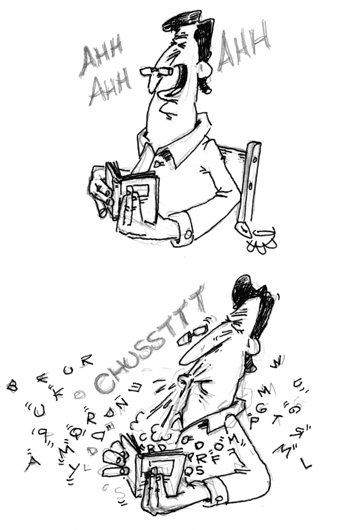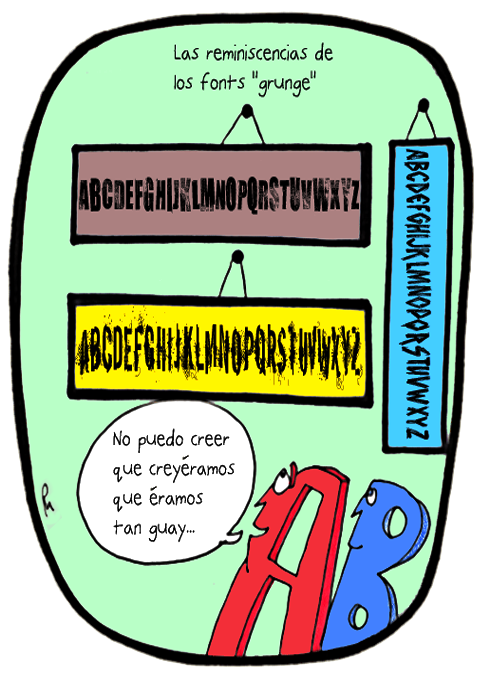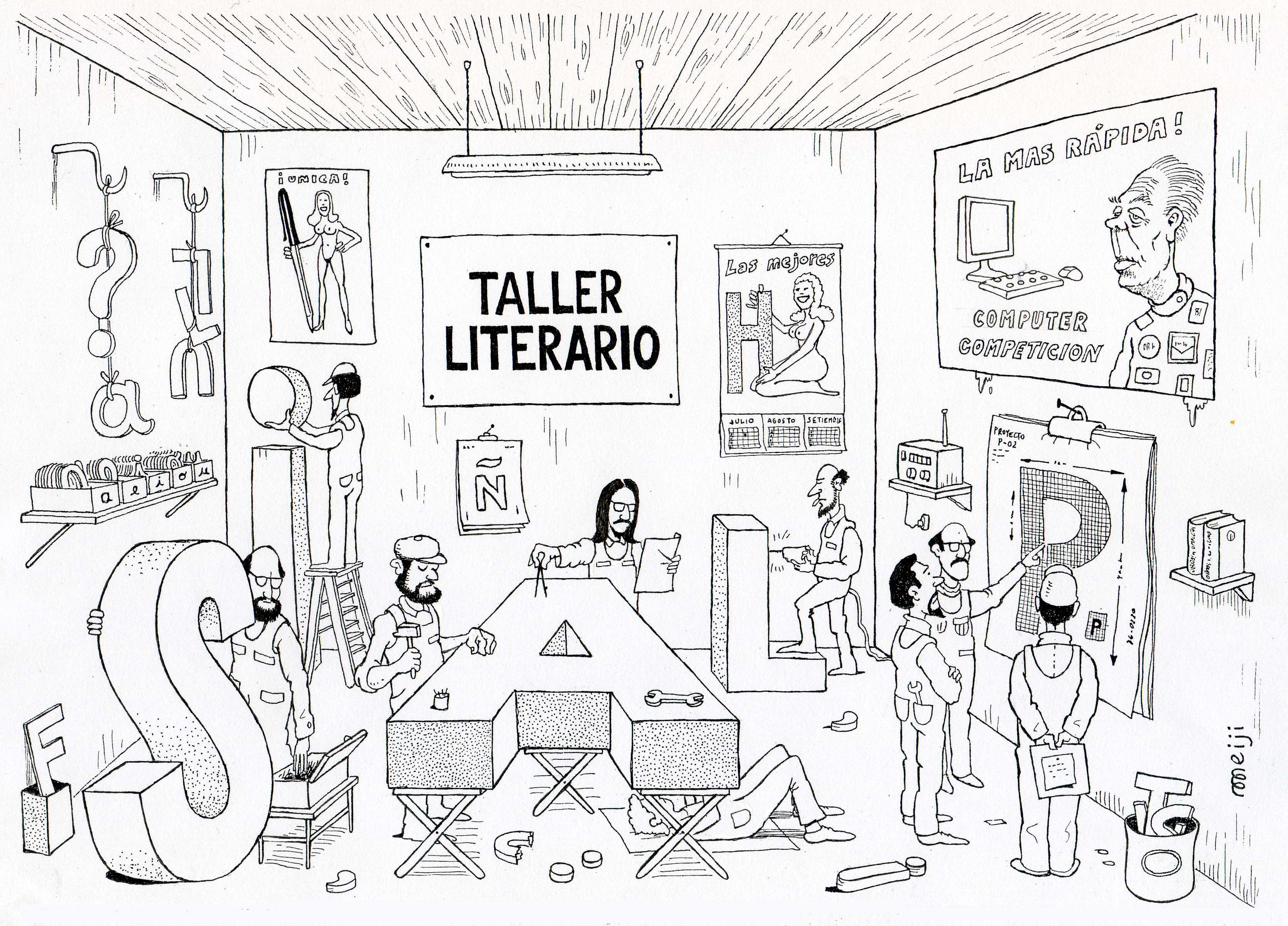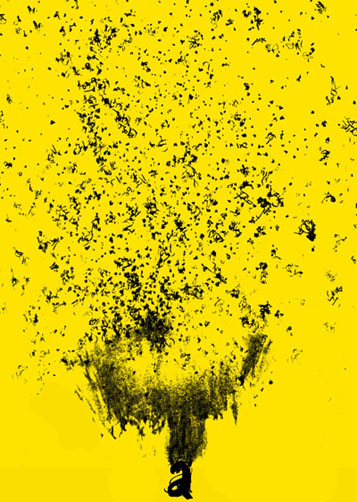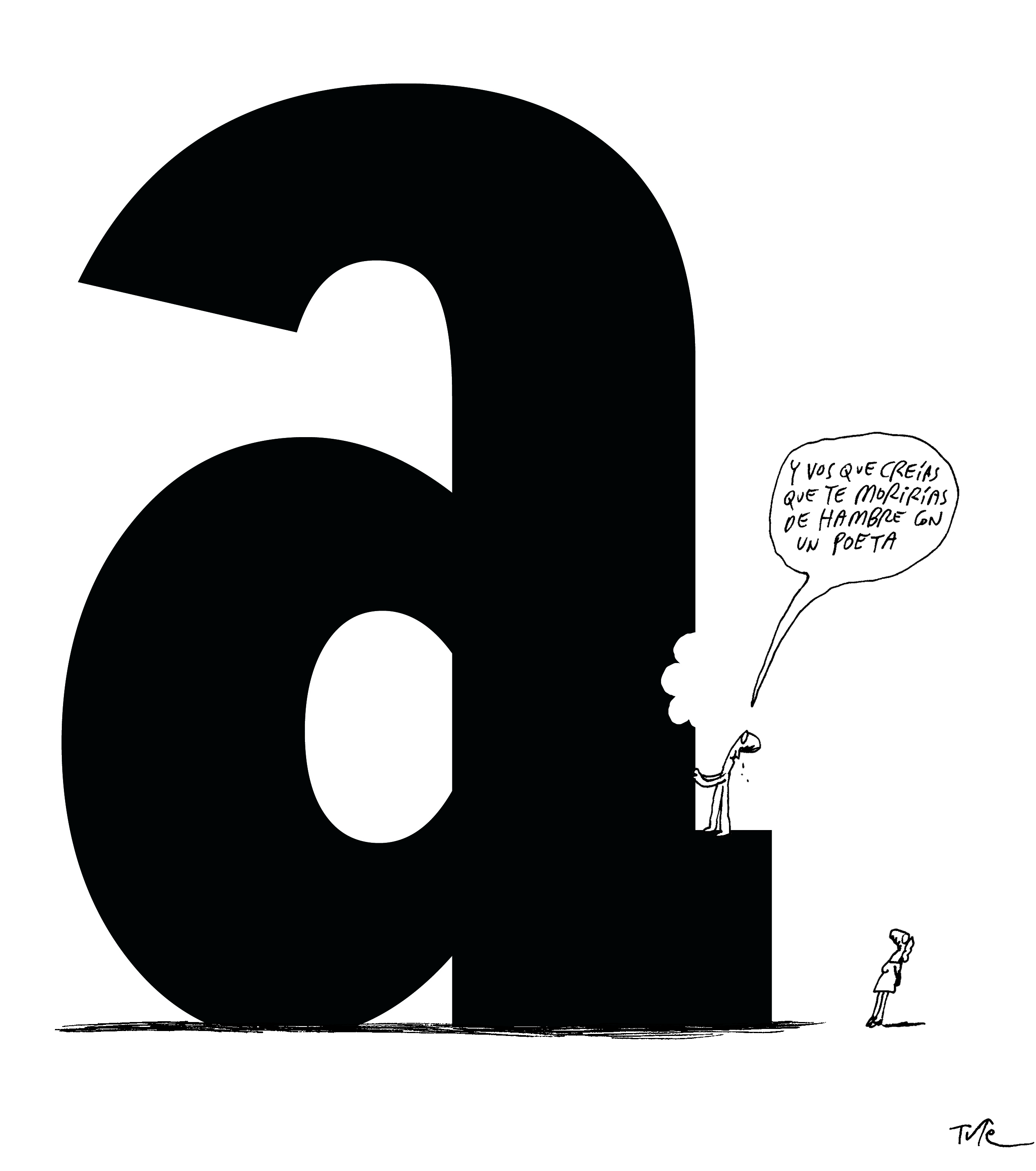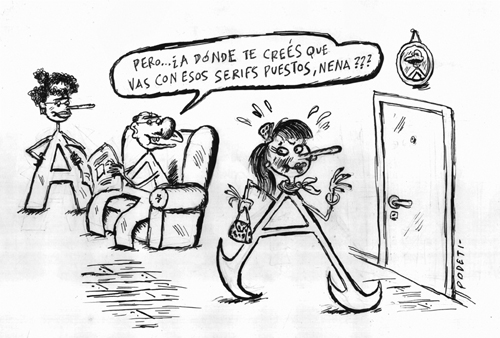
Letras de humor. Letras ilustradas
Una serie (poco seria) de miradas ocurrentes sobre la letra y la tipografía. El humor, la reflexión poética, la acidez como instrumento, el estallido del código. Guiños de Steinberg, sombras de Brossa, yeites de Pacovská.
Les presentamos otros animales gráficos de parecida sed.
Inaugura la sección Pollux, que ya colaboró con nosotros en el Glosario.
Paul Morris nació un 19 de junio de 1979 en Beverley, Inglaterra, pero es un dibujante estadounidense.
Hijo de madre canaria y padre galés, se crió en Los Ángeles, California. Estudió Historia en UCLA (Los Ángeles), Brown University (Providence) y en el Instituto de Arte de California, arte y diseño gráfico.
Dibuja el cómic diario “The Wavy Rule" para emdashes.com y es el autor de las novelas gráficas Ferrex and Porrex y The Golden Helmsman.
Wright es dibujante, humorista y autor de historias, poesías y juegos para chicos.
También ha diseñado juguetes y, de vez en cuando, compone y graba sus canciones.
Miguel Repiso, nació en Buenos Aires en 1961 y con palabras de Quino sabemos que “exhibe extrañas cartas de identidad que lo muestran primo de García Lorca, hermano de Edward Munch, compadre de Boris Vian y yerno de Cátulo Castillo.” |
Jorge Mejide nació en San Fernando, (Buenos Aires), el 1º de Octubre de 1947.
Participó en numerosas exposiciones en el país y en el extranjero.
Recibió entre otros premios, en 2005: Mención de Honor, Salón OSDE. 2003: Premio Fundación Huesped. 2002: 1er Premio Salón Nacional de Dibujo y Grabado de Entre Ríos. |
Juan Lima, artista visual, poesía, libros, ilustración, objetos, premios, afiches, publica, expone, pixela, chirría, ilustra, "cita", serrucha, inventa y más.
Nació en El Perdido, vive en San Telmo, sobrevuela Traslasierra. Casi siempre ojos verdes. Así es. |
Tomás Gimbernat
nació en 1974 y vive en Puerto Madryn desde entonces. Dibujante, caricaturista, artista plástico y también algo músico.
Dibuja desde que tiene uso de razón. Cursó sus estudios de Bellas Artes en Mendoza, Bahía Blanca y Trelew. Sus dibujos fueron publicados en varios medios gráficos nacionales e internacionales, también en medios virtuales. Actualmente coordina talleres de grabado, dibujo artístico e historieta para niños, adolescentes y adultos. Participa en ferias de artesanos como caricaturista urbano y publica junto a los dibujantes patagónicos de La Duendes.
Juan Matías Loiseau
nació el 21 de mayo de 1974 en Buenos Aires, Argentina.
Estudió un poco de diseño gráfico, un poco de humorismo y de cine.
Parte de su universo, la encontrás en Tutelandia. |